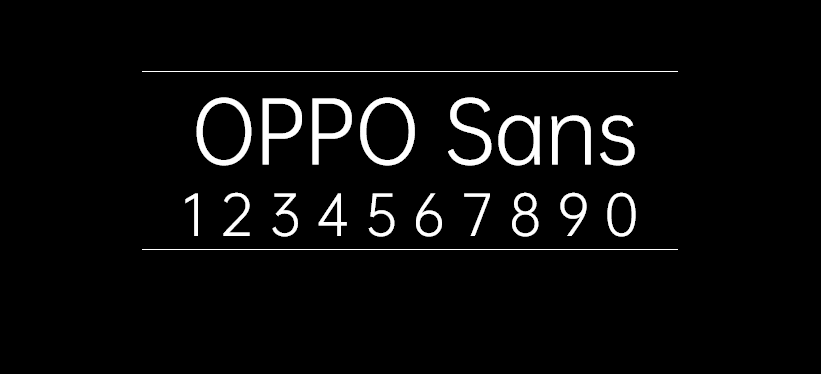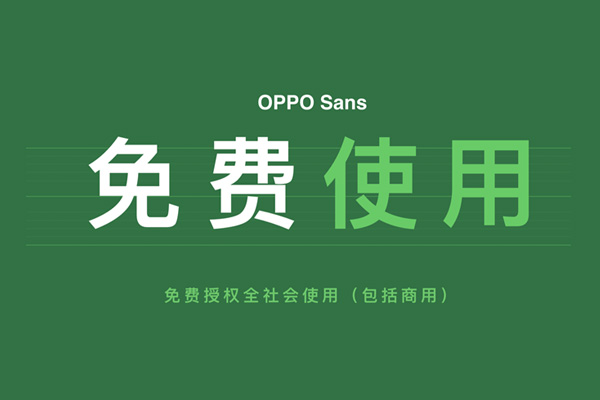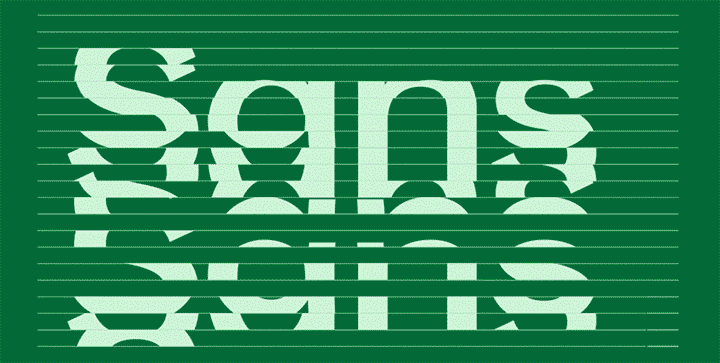
OPPO Sans
OPPO Sans 早在四月份就已经发布,最早适用于ColorOS6 上,是由汉仪字库定制的OPPO品牌字体。作为OPPO 全新品牌字体OPPO Sans采用了全新骨架,中宫自然舒适,结构稳定,字形舒展,强化了屏幕显示的易读性和外观性,简洁真实,体现了科技美感。据汉仪字库介绍该品牌字体中文部分由汉仪字库字体设计师黄珍元完成 , 西文部分由英国 Pentagram 公司设计。西文部分同时由汉仪字库西文项目负责人张暄协作完成,帮助OPPO从品牌理念出发用文字全方位探索科技美感。
这款品牌字体包含的字符高达226003个共11个语种同时覆盖21个国家语言 , OPPO将其定位为全球化品牌字体。